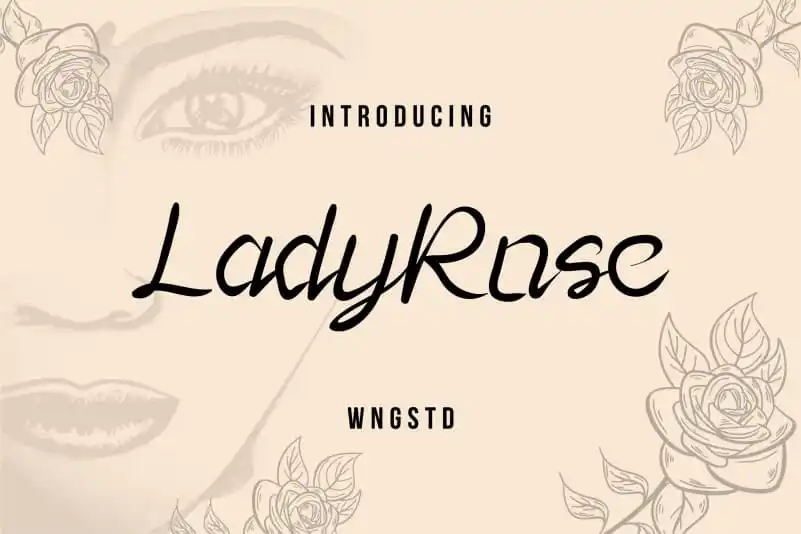
Lady Rose Calligraphy Typeface – Download Grátis
Lady Rose Calligraphy Typeface é uma tipografia script leve e moderna que oferece suporte a todos os caracteres do idioma inglês. A escolha dessa fonte pode ser ideal para projetos tradicionais ou digitais, especialmente para quem gosta de fazer trabalhos artesanais ou criar arte gráfica. Este tipo de letra é perfeitamente compatível com qualquer ferramenta e seu charme brincalhão faz dela uma escolha ótima para criações inspiradoras como painéis de avisos, além de ser excelente para comunicar sua marca. Lady Rose Calligraphy Typeface é um recurso gráfico que pode ser usado em inúmeras aplicações diferentes.